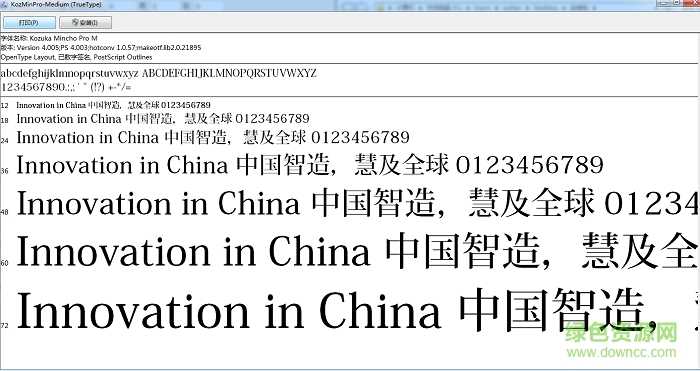
kozuka mincho pro m 字體又稱kozminpro-medium字體,字形流暢大方,筆畫自然,視覺效果突出,大家按照以下步驟安裝后就可以使用了,歡迎大家在綠色資源網(wǎng)免費下載!
【宋體】
北宋的畢升發(fā)明了活字印刷,刻字在楷書體上產(chǎn)生了一種橫輕直重,閱讀醒目的印刷體,后稱宋體。到了明宋代演變?yōu)楣P劃橫細堅粗,字形方正的明體。當時民間流行一種橫劃很細,而堅劃特別粗壯,字形扁扁的洪武體,如職官的銜牌、燈籠、告示等都采用這種字體。特點:橫細堅粗,“撇如刀,點如瓜子,捺如掃”筆劃嚴謹,帶有裝飾性的點線,字形方正典雅,嚴肅大方,是美術(shù)字體之首。
【仿宋體】
出現(xiàn)了筆畫粗細一致,講究頓筆,挺拔秀麗,適合手寫體的仿宋體,當時稱為新宋,宋體又稱為老宋。是現(xiàn)代宋體的一種。特點:字身秀長、宋楷結(jié)合、橫斜豎直、粗細一樣、間隔均勻,起筆頓頓,落筆頓頓。